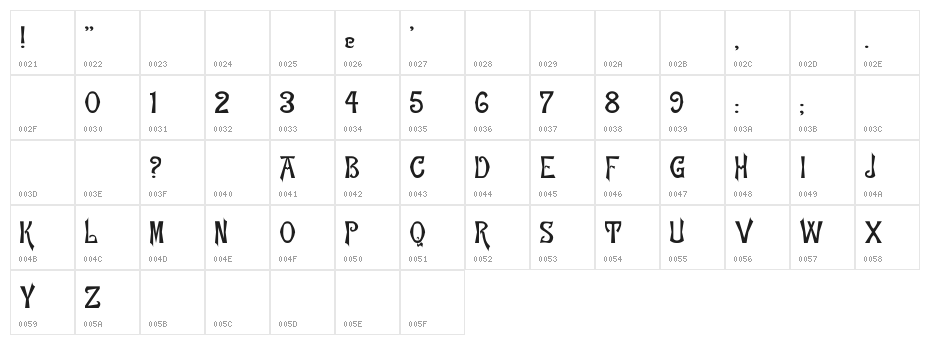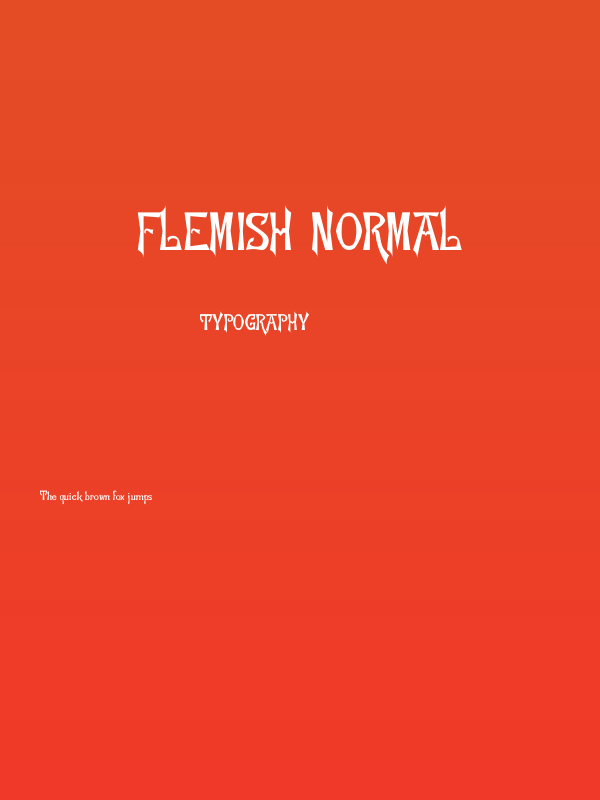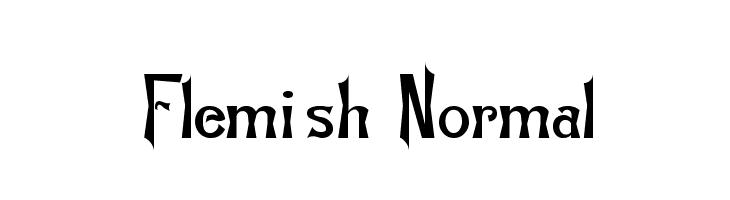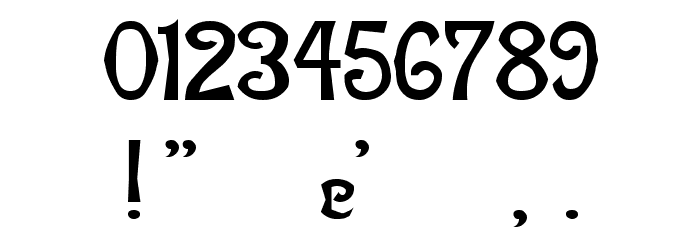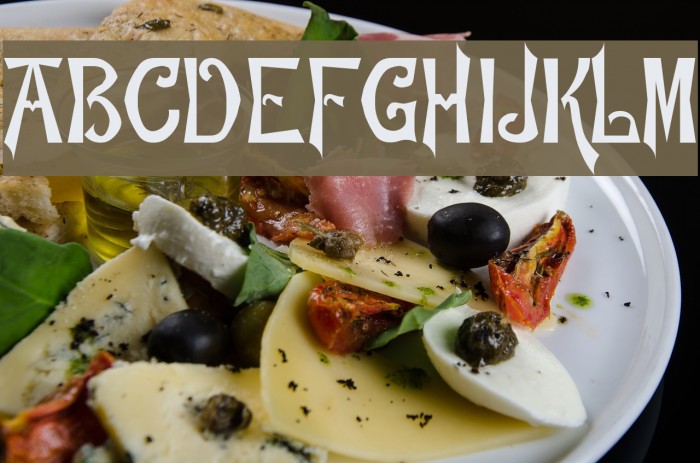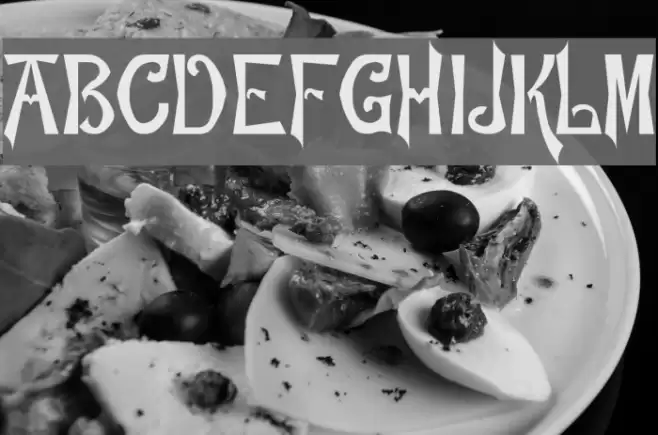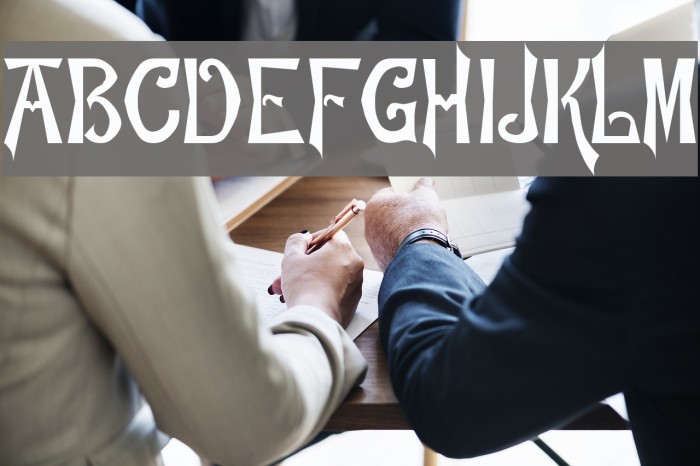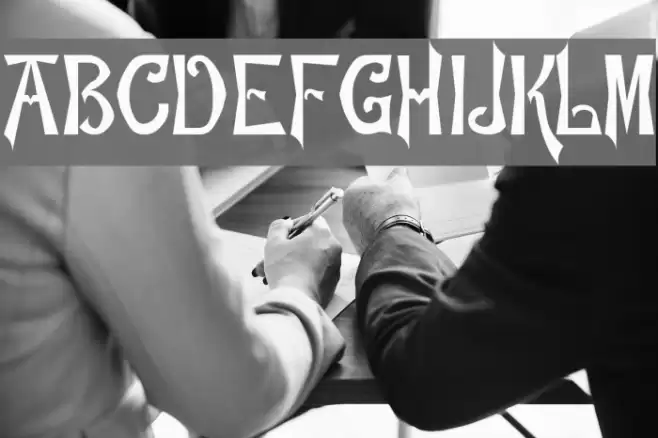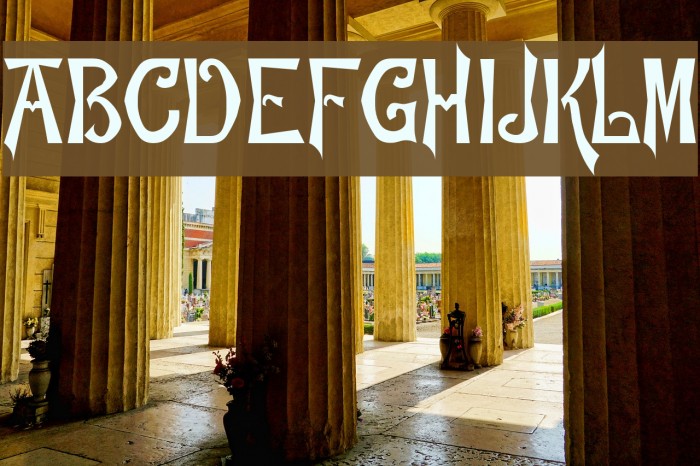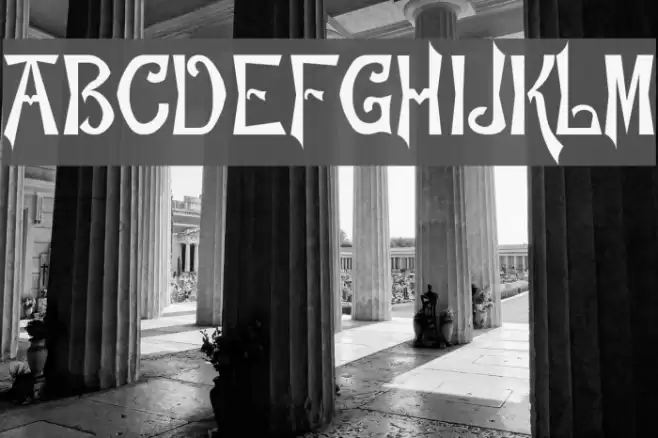
Flemish-Normal Font
| Gesamtstil | Gothic, Medieval, Decorative |
| Vorgeschlagene Projekte | Ideal for fantasy book covers, historical event posters, themed invitations, or any project requiring a medieval or gothic touch. |